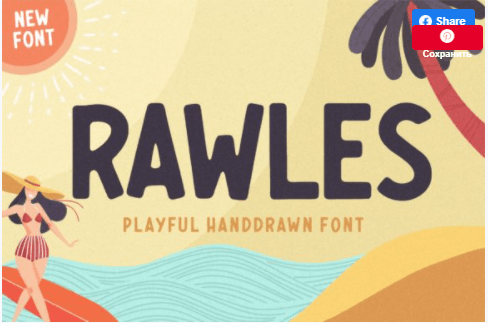
Rawles Font
Rawles - яркий и игривый дисплейный шрифт. Добавьте этот шрифт в винтажном стиле к своему творению. Независимо от темы, этот шрифт станет невероятным активом в вашей библиотеке шрифтов, так как он может улучшить любое творение.